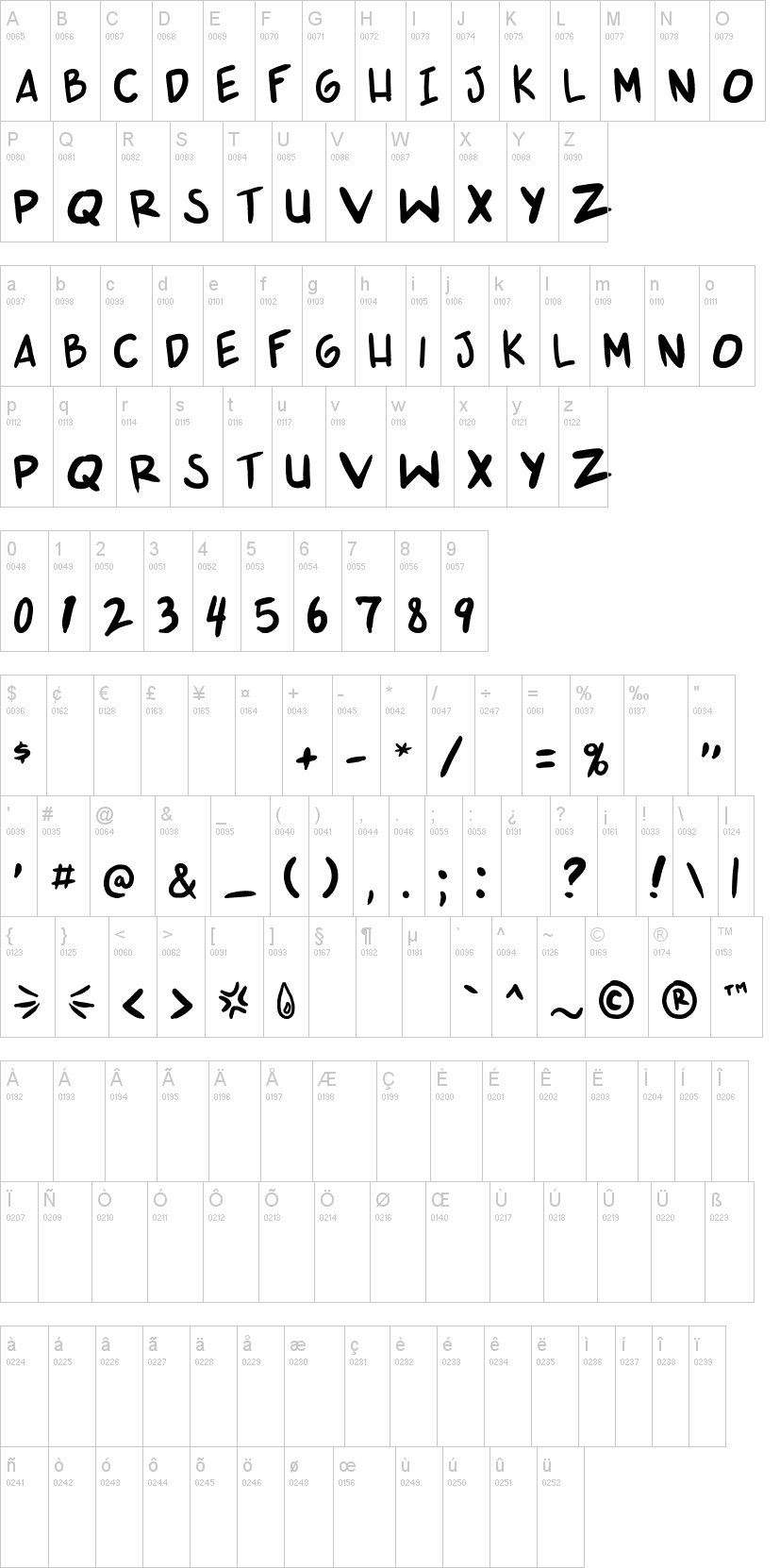
Shonen Punk v2 是一款受日本漫画启发的字体,它具有柔和的色彩和流畅的线条,适合用于标题、标签、海报、海报等。它具有良好的可读性,可以帮助你轻松创建出有趣的设计。它的字体设计精细,可以增强设计的美感,使你的作品更加出色。内容介绍
Shonen Punk v2是一款非常不错的手写艺术字体,具有很好的视觉感,适合于文化类的宣传设计、商业类品牌的广告和产品包装设计以及个性化文字排版等较多场景。